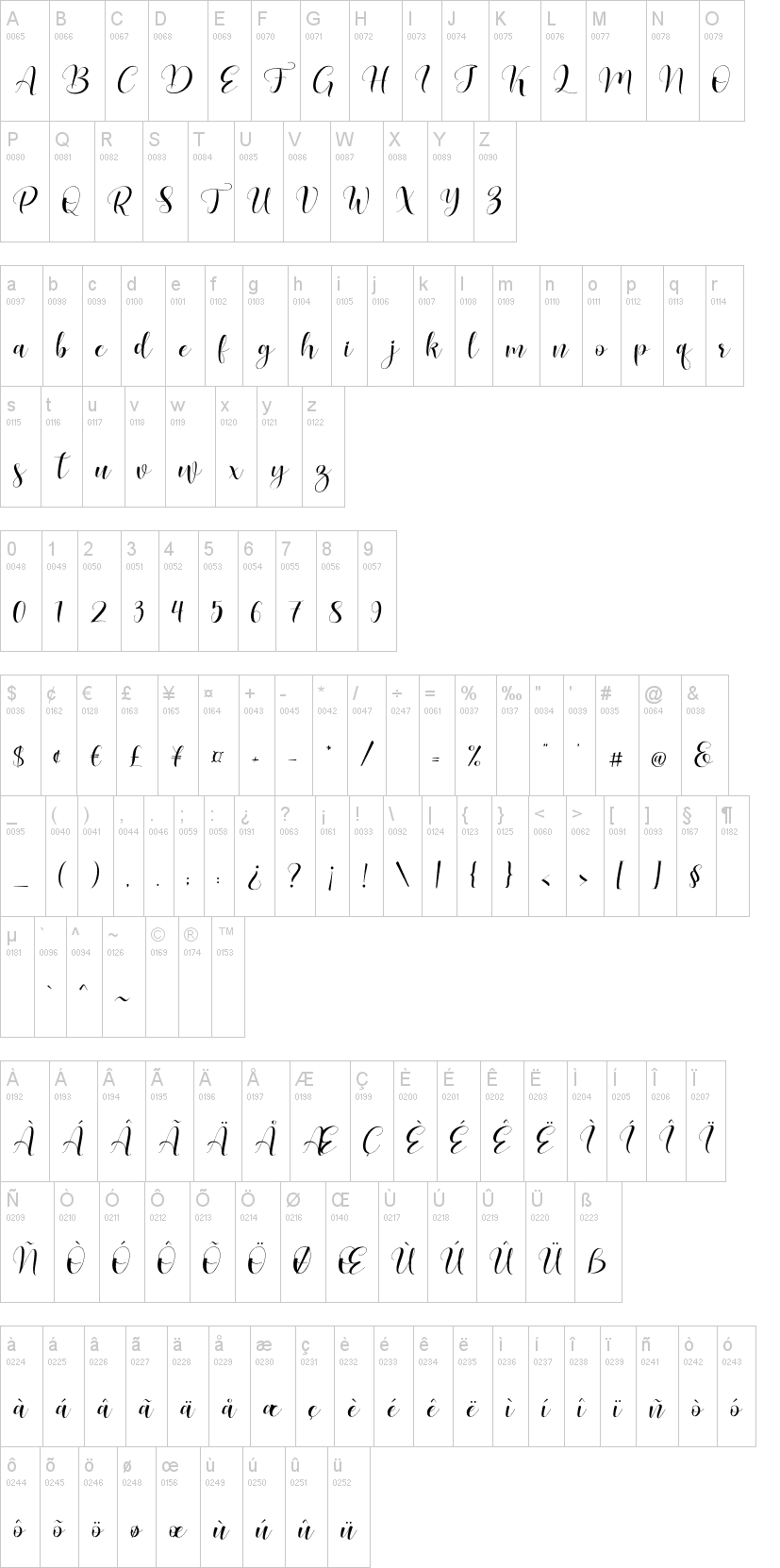
Lovea 字体是一款复古的欧文字体,它的特点是字体设计精美,笔画细腻,衬线精细,小写字母特别美观,整体给人一种古朴的感觉,可以用于印刷品、海报、书籍、网页等多种场景。内容介绍
Lovea是一款非常不错的手写艺术字体,具有很好的视觉感,适合于文化类的宣传设计、商业类品牌的广告和产品包装设计以及个性化文字排版等较多场景。